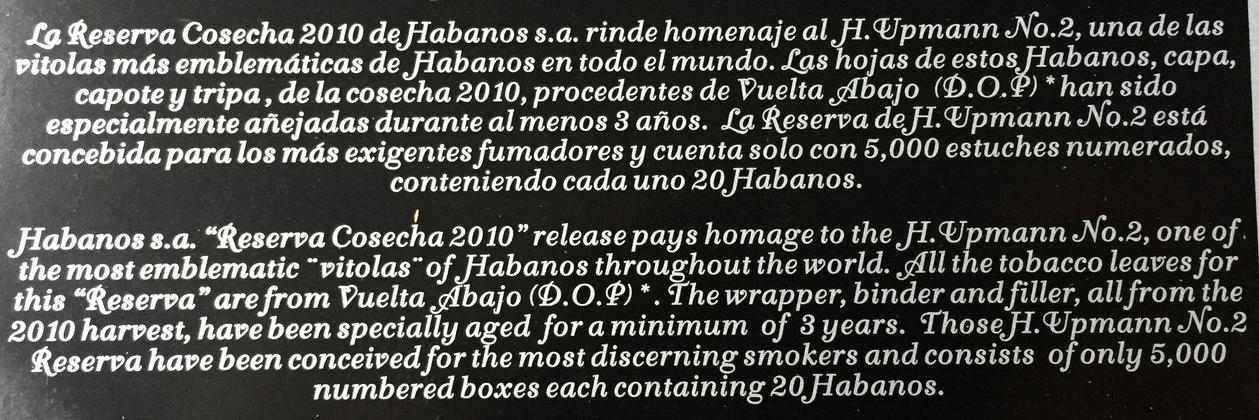
Suche Schriftart von kubanischer Zigarrenbanderole
Ich würde gerne wissen welche Schriftart auf der Banderole verwendet wurde. Die beiden "R" in der Mitte scheinen eine andere Schriftart zu sein als das "Habana Cuba" oder? Die Banderole wurde bei besonderen Zigarren aus Kuba verwendet.
Century Schoolbook mit Swashes?